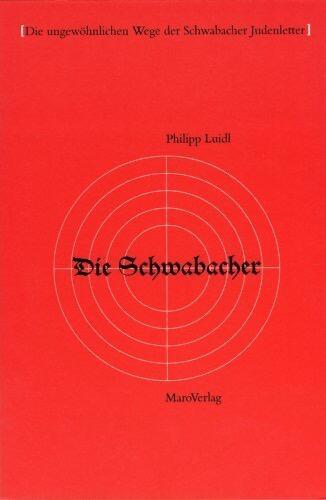
Wie jede Schrift hat auch die Schwabacher ihre Geschichte. Der bekannte Typograph Philipp Luidl erzählt sie mit vielen Bildbeispielen bis hin zu dem Tag, an dem Hitler die Schwabacher Judenlettern 1941 verbot (und warum!)
Eine zackige Kehrtwendung. Paßt die Fraktur zu Frauenschönheit und Männerkraft? Philipp Luidl geht der sogenannten Schwabacher Judenletter nach
Warum haben wir länger als andere europäische Völker die Fraktur als Normschrift gedruckt und Kurrentschrift als Handschrift geschrieben, so lange, daß viele sie für die deutsche Schrift schlechthin halten? Und warum schreiben und drucken wir heute in Antiqua? Sowohl das lange Festhalten an den gebrochenen Schriften als auch den plötzlichen Umschwung zur Antiqua verdanken wir weltanschaulichen Kämpfen, die sich über mehrere Jahrhunderte hinzogen. Erst die Nationalsozialisten etablierten die Antiqua in Deutschland endgültig.
Adolf Hitler konferierte am 3. Januar 1941 mit Max Amann, Verleger und Herausgeber des „Völkischen Beobachters“, Präsident der Reichsschrifttumskammer, Reichsleiter für die Presse der NSDAP, und mit dem Druckereibesitzer Adolf Müller, der den „Völkischen Beobachter“ druckte. Die Expertenrunde entschied, die Antiqua als „Normal-Schrift“ im Reich durchzusetzen. Zuerst sollten die im Ausland verbreiteten oder für eine Auslandsverbreitung vorgesehenen Zeitungen und Zeitschriften umstellen.
Erklärt wurde diese Entscheidung so unsinnig, daß die Begründung später, zur Umstellung der Schulbücher, kaum noch erwähnt wurde. In der Mitteilung vom Stabsleiter beim Führerstellvertreter, Martin Bormann, heißt es also: „In Wirklichkeit besteht die sogenannte gotische Schrift aus Schwabacher Judenlettern. Genau wie sie sich später in den Besitz der Zeitungen setzten, setzten sich die in Deutschland ansässigen Juden bei der Einführung des Buchdrucks in den Besitz der Buchdruckereien und dadurch kam es in Deutschland zu der starken Einführung der Schwabacher Judenlettern.“
Das war eine zackige Kehrtwendung. Reichsinnenminister Frick hatte noch am 9. Mai 1933 in einer Ansprache an die Kultusminister der Länder verlangt, daß die „deutsche“ Schrift, womit er die gebrochene meinte, ihren unbedingten Vorrang vor der lateinischen Schrift niemals verlieren solle. 1937 wurde jüdischen Verlagen die Verwendung der Fraktur sogar verboten. Plötzlich sollten das „Schwabacher Judenlettern“ sein?
Man stand 1941 vor dem langen Marsch nach Osten, und die gebrochenen Typen waren ungeeignet für internationale Propaganda. Sie erschwerten außerdem die Kommunikation in den besetzten Gebieten, denn Polen und Franzosen konnten die Befehle und Dokumente in gebrochenen Schriften nicht lesen. Die Altertümlichkeit der Schrift vertrug sich außerdem nicht mit den modernen Ideen des nationalen Sozialismus.
Hitler und seine global denkenden Propagandisten haben sich den Begriff „Schwabacher Judenlettern“ ausgedacht. Aus jüdischen Druckereien konnten keine gebrochenen Schriften in Deutschland kommen, denn nur Christen mit Bürgerrecht durften um 1500 Druckereien führen, als die Schwabacher sich verbreitete.
Der Typograph Philipp Luidl hat jetzt eine bislang kaum publizierte These aufgegriffen, wie der Ort Schwabach, wo sich erst 1603 eine Druckerei erstmals nachweisen läßt, zur Ehre des Namensgebers kam. Es sei zur Klärung ein Blick geworfen auf die vier verschiedenen Typen gebrochener Schriften, die sich aus den handgeschriebenen Typen der Gotik entwickelten: Die Mutter aller gebrochenen Schriften war die aus Paris kommende dunkle, stark gebrochene, verzierte Gotisch, Textur genannt, die Gutenberg mit Fust und Schöffer um 1454 zum Vorbild für die Bleilettern zum Druck der 42zeiligen Bibel nahmen. Der Textur folgte um 1485 die weniger stark gebrochene Rundgotisch, auch Rotunda genannt, die sich vor allem in Südeuropa verbreitete. In Deutschland entwickelten sich gleichzeitig drittens die breitlaufende, volkstümliche Wittenberger und Schwabacher und regional weitere Formen; nur die Schwabacher wird heute als eigene Type klassifiziert. In der Renaissance schließlich entstand jene schmalere, zierliche Schrift, die wir als die Fraktur im engeren Sinne bezeichnen. Sie wurde die deutsche Verkehrsschrift bis ins 20. Jahrhundert.
Warum blieb die Fraktur in Deutschland so lange als Verkehrsschrift erhalten? Um 1600 war in Frankreich, Italien, Spanien und auch in England der Wandel zur Antiqua vollzogen, denn die Schrift der römisch-katholischen und anglikanischen Kirche war die humanistische Minuskel. Die deutschen Katholiken konnten sich Rom darin nicht anschließen (obwohl an einigen deutschen Lateinschulen Antiqua geschrieben wurde), weil sie, beeindruckt von den Reformisten, an der Kurie zweifelten und sie die Volkstümlichkeit der Bibelübersetzungen in Frakturschrift überzeugte. Die deutschen Gegner der Fraktur waren nicht Katholiken, sondern Humanisten, die sich von Martin Luther abgewandt hatten wie Erasmus von Rotterdam. Die deutschen Humanisten schrieben in Antiqua, sowohl in der Annahme, dies sei die Schrift der Antike gewesen, als auch in dem Gefühl der Verbundenheit mit der europäischen Bildungsgemeinschaft. Die lutherischen Reformisten ließen ihre Texte in der breiten Schwabacher Type drucken, damit jeder sie lesen konnte, und diese Schrift verbreitete sich rasch. Luidl ist der Quelle nachgegangen, welcher der Name „Schwabacher“ für die Type der Luther-Zeit entnommen wird: einem Lehrbuch für Schönschrift von Wolfgang Fugger aus dem Jahr 1553. Der Name der Schrift scheint auf einen politischen Text hinzudeuten: Die „Schwabacher Artikel“ gingen als Ergebnis des Schwabacher Konvents vom Oktober 1529 und als Darstellung der protestantischen Lehrinhalte ein in die Confessio Augustana von 1530. Darin hatten die Protestanten ihre Bekenntnisse für den Augsburger Reichstag gesammelt, der vom Kaiser zur Rettung der Glaubenseinheit einberufen worden war. Die Schwabacher Artikel wurden in Augsburg mit jener breiten Drucktype gedruckt, die man später nach diesen Artikeln benannte. Bewiesen ist diese These nicht, aber sie klingt besser als die, wonach der Augsburger Drucker und Schriftschneider aus Schwabach stammte, wofür es auch keine Belege gibt.
Luidl springt von 1530 leider direkt in das ungebildete Gerede der Nationalsozialisten und läßt die Chance ungenutzt, seine These zu untermauern oder den hochinteressanten Schriftenstreit zwischen 1600 und 1941 darzustellen, zu dem sich jeder Schriftsteller und Gelehrte in diesen Jahrhunderten Gedanken machen mußte. Zwischen Goethe und seiner Mutter beispielsweise entstand ein brieflich belegter Disput die Mutter liebte die Fraktur, Goethe hielt die Antiqua für die Schrift der Gebildeten, ließ aber in beiden Schriften drucken.
Statt dessen stellt Luidl eher unerhebliche Mutmaßungen an, wo Hitler und seine Experten den Namen Schwabach in jüdischem Kontext gehört haben könnten. Ein Bankhaus vielleicht?
Daß Hitler die gebrochenen Schriften nicht mochte, zeigt Luidl an einem Beispiel: ein Wettbewerb für einen Urkunden-Entwurf. Hitler entscheidet sich für die Futura, eine serifenlose, moderne Schrift. Luidl führt dazu nichts weiter aus, dabei ist diese Geschichte hochinteressant und unterstreicht Hitlers modernen Geschmack. Die Futura war 1928 unter den Händen Paul Renners entstanden mit dem etwas absurden Anspruch, die Schrift dieser Zeit zu sein. Sie war zwar den Bauhaus-Leuten noch viel zu harmonisch, vor allem die späteren Varianten, die wir noch heute benutzen, aber sie wurde im Bauhaus verwendet, weil es nicht viel anderes ohne Serifen gab. Hitlers Leute, so Luidl, nannten Renner einen Kulturbolschewisten, machten da also keinen Unterschied, weil sie eigentlich der Fraktur anhingen. Hitler selbst differenzierte gewiß unbewußt zwischen Renner und Bauhaus, wenn er die Futura anderen Schriften vorzog und gegen das Bauhaus wetterte: „Das ganze Kunst- und Kulturgestotter von Kubisten, Futuristen, Dadaisten usw. ist weder rassisch begründet noch volklich erträglich.“ Das sagte er in seiner Rede am 6. September 1934 auf der NSDAP-Kulturtagung im Nürnberger Apollo-Theater. Hitler sah die Deutschen in antiker Tradition, er geißelte „Straßenbenennungen und Maschinenschrift in echt gotischen Lettern“ und rief über „jene Rückwärtse“ aus: „Sie haben keine Ahnung davon, daß deutsch sein, klar sein heißen könnte, sonst würden sie sich besser als Versteinerungen in die Museen zurückziehen, denn als aufdringliche Geister die Mitwelt erschauern zu lassen.“ Etwas später: „So wie wir aber in unserem übrigen Leben dem deutschen Geist die freie Bahn zu seiner Entwicklung gaben, können wir auch auf dem Gebiete der Kunst nicht die Neuzeit zugunsten des Mittelalters vergewaltigen. Eure vermeintlich gotische Verinnerlichung paßt schlecht in das Zeitalter von Stahl und Eisen, Glas und Beton, von Frauenschönheit und Männerkraft, von hochgehobenem Haupt und trotzigem Sinn." Die Gotik war Hitler unheimlich.